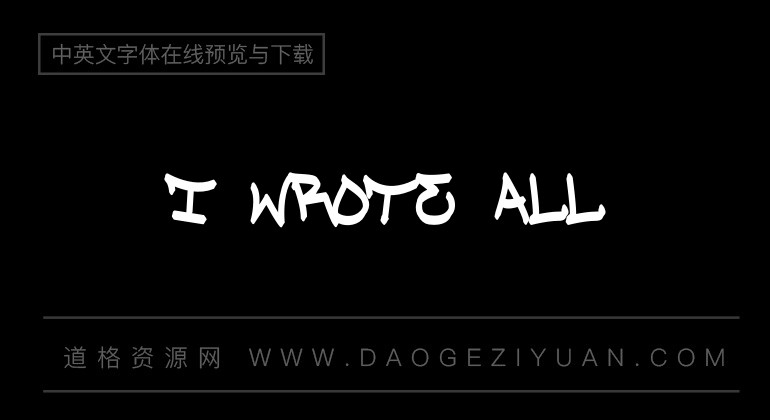
I Wrote All 是一种手写风格的英文字体,它的特点是每个字母都像是由手写而成,给人一种自然的感觉。这种字体的笔画非常有特色,每个字母的线条都非常流畅,而且有些笔画甚至带有一些颤动,使得整个字体看起来非常有生命力。 I Wrote All 字体最初由设计师 Ian Barnard 手写而成,后来经过数字化处理成为了一种可供电脑使用的字体。这种字体非常适合用于设计海报、书籍封面、广告宣传等场合,它既有手写字体的独特魅力,又有数字字体的清晰度和易读性。 总之,如果你想要在设计作品中加入一些自然、温暖的元素,那么 I Wrote All 字体是一个非常不错的选择。内容介绍
I Wrote All是一款非常不错的手写艺术字体,具有很好的视觉感,适合于文化类的宣传设计、商业类品牌的广告和产品包装设计以及个性化文字排版等较多场景。